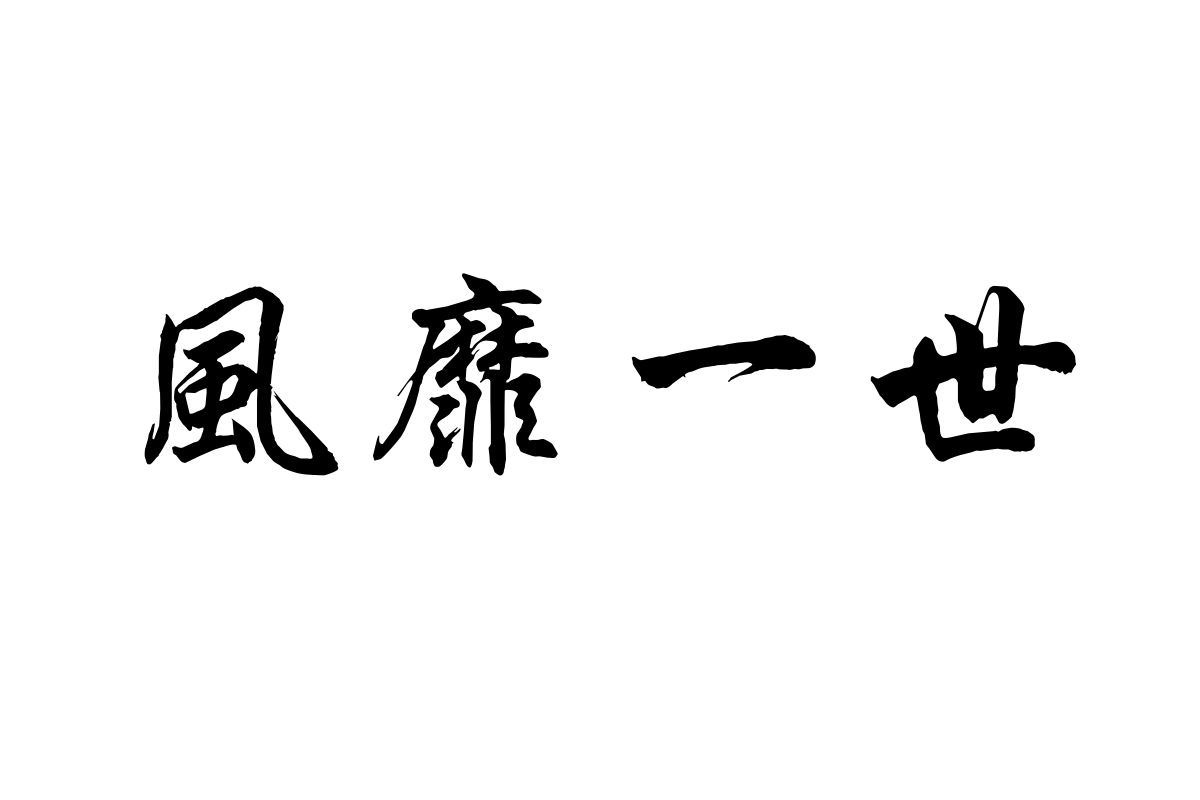
汉仪行楷繁体是一套由汉仪公司开发的中文字体,主要用于印刷和排版。这套字体的特点是笔画流畅、结构紧凑,适合用于标题、正文等需要清晰易读的文本。
汉仪行楷繁体的每个字符都经过精心设计,使得字形规整、美观大方。同时,这套字体也具有较高的可读性,无论是在黑白还是彩色的纸张上都能保持良好的视觉效果。
除了常规的宋体、黑体外,汉仪行楷繁体还提供了多种特殊效果,如斜体、手写体等,以满足不同场景的需求。此外,这套字体还支持多种字号和字体样式,方便用户根据自己的需求进行选择。
总的来说,汉仪行楷繁体是一款功能强大、适用范围广泛的中文字体,适合用于各种印刷和排版工作。